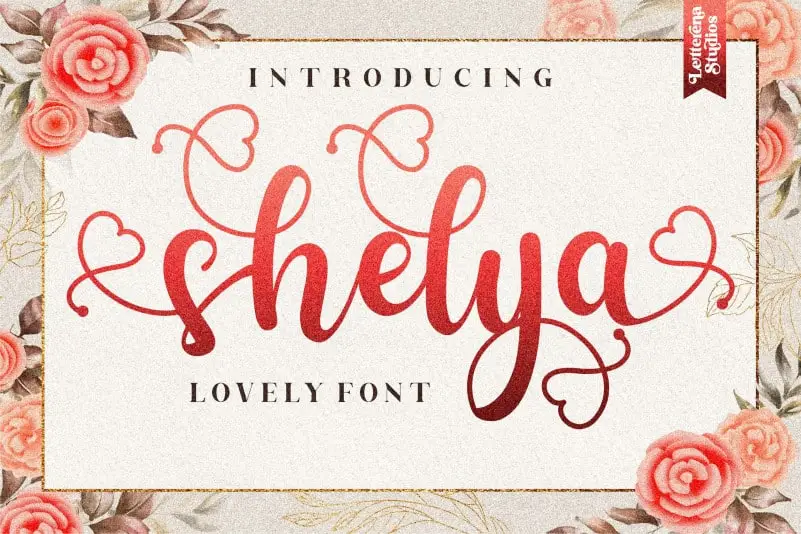
Shelya Calligraphy Font – Download Grátis
A Shelya Calligraphy Font é uma delícia para designers apaixonados por escrita cursiva. Com seu belo equilíbrio entre elegância e fluidez, ela se destaca como a escolha perfeita para diversos tipos de projetos gráficos. Perfeitamente adaptada para anúncios de casamento, cartas de gratidão, frases inspiradoras ou até mesmo logotipos e cartões de visita, essa fonte oferece uma atmosfera autêntica que encaixa-se perfeitamente em qualquer projeto que valorize um toque pessoal. Com seu desenho único e sua linha suave, a Shelya Calligraphy Font traz um brilho especial à seus projetos de design. Além disso, os detalhes cuidadosamente criados como alternativas únicas garantem uma variedade infinita que pode ser usada para criar designs incrivelmente distintos ou simplesmente exaltar o estilo e a personalidade da sua marca. Sem dúvida alguma, esta fonte é um trunfo indispensável para qualquer designer buscando dar um toque especial a suas criações.